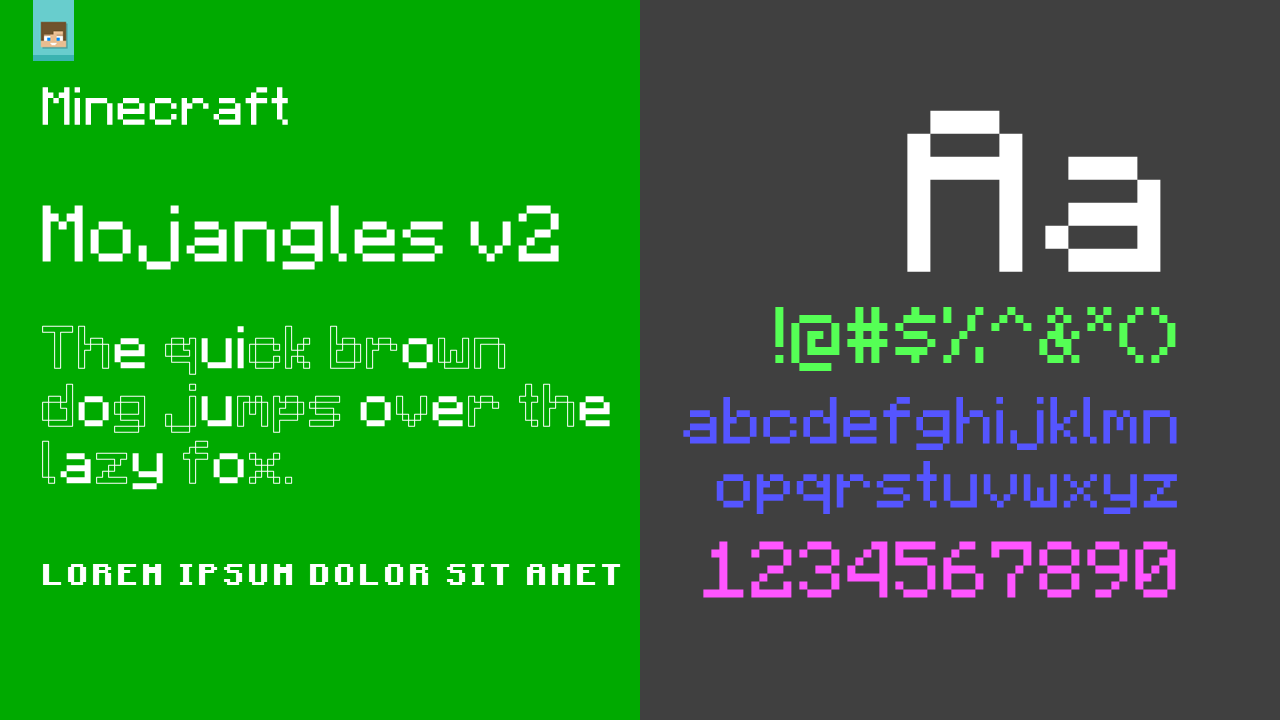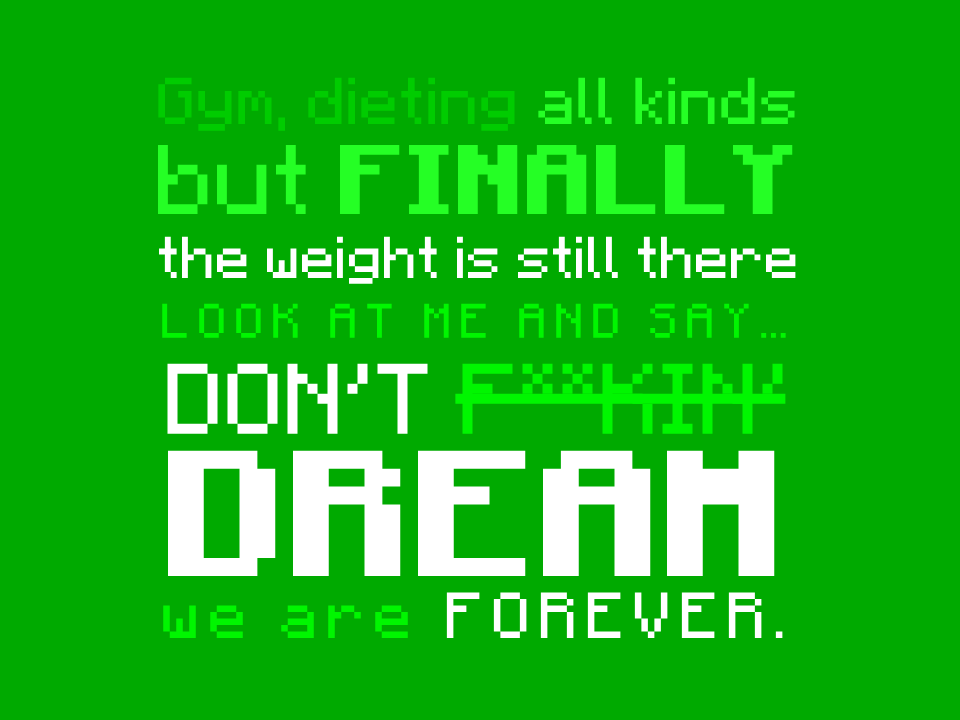
Это наш первый шрифт, скоро появится шрифт без засечек. Следите за новостями!
This is our first font, sans-serif will be coming soon. Stay tuned!
Bold font updated, check it out!
If its three accents, letters will be BELOW THE BASELINE!
false. the above screenshot was taken while playing java minecraft with no resource packs. the red line points to the baseline, being represented in a faint black colour.
I hate asterisks only censors!